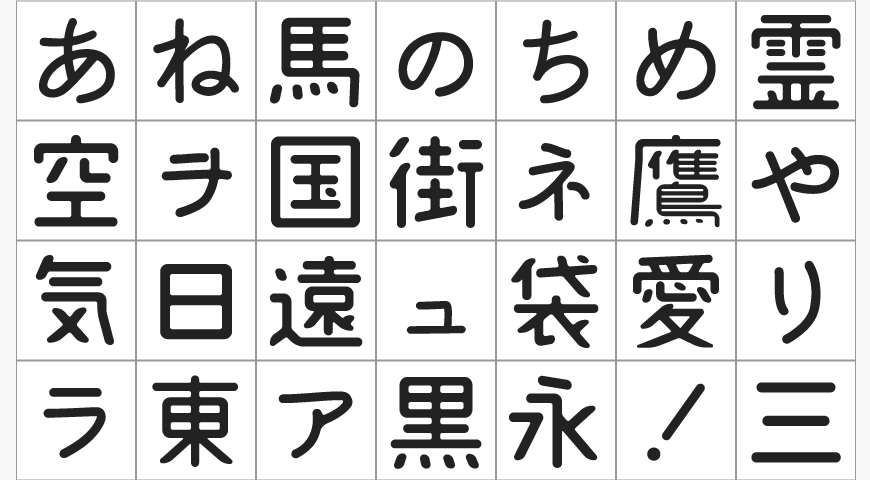
这次来分享一款大家可能会喜欢的日文字体「 甜瓜体 」(日文名:マメロン),作者说应该叫做哈密瓜体。虽说这是一款日文字体,但是收录超过6,600个字 (JIS第1水准2965字,第2水准3390字) ,等于说支持灰常灰常多的中文字,而且用起来的样式可爱可爱的,一点都不输给 「 濑户字体 」 ,当然这还是取决于大家自己的喜好啦!如果喜欢这款字体就赶紧下载吧!